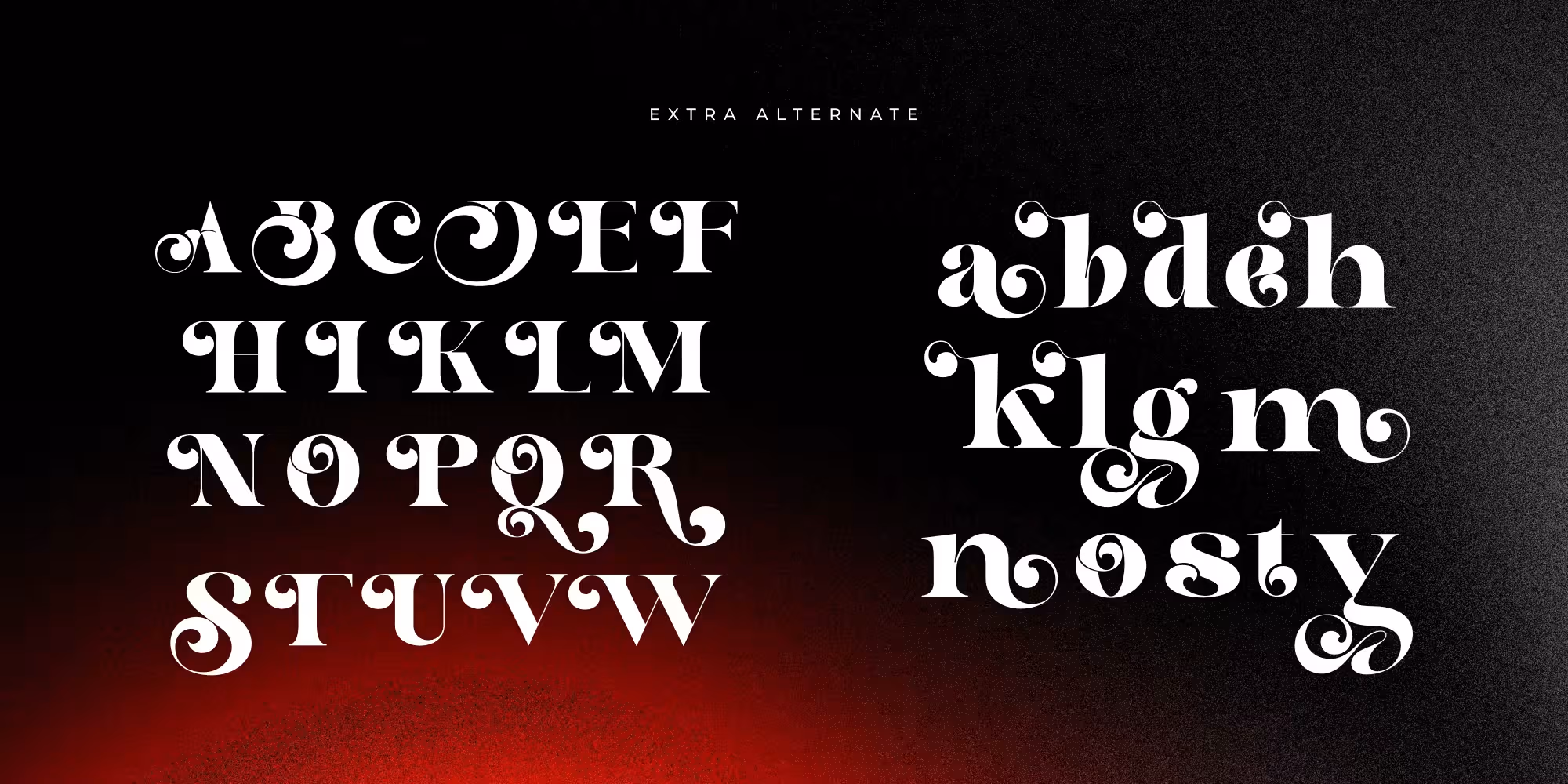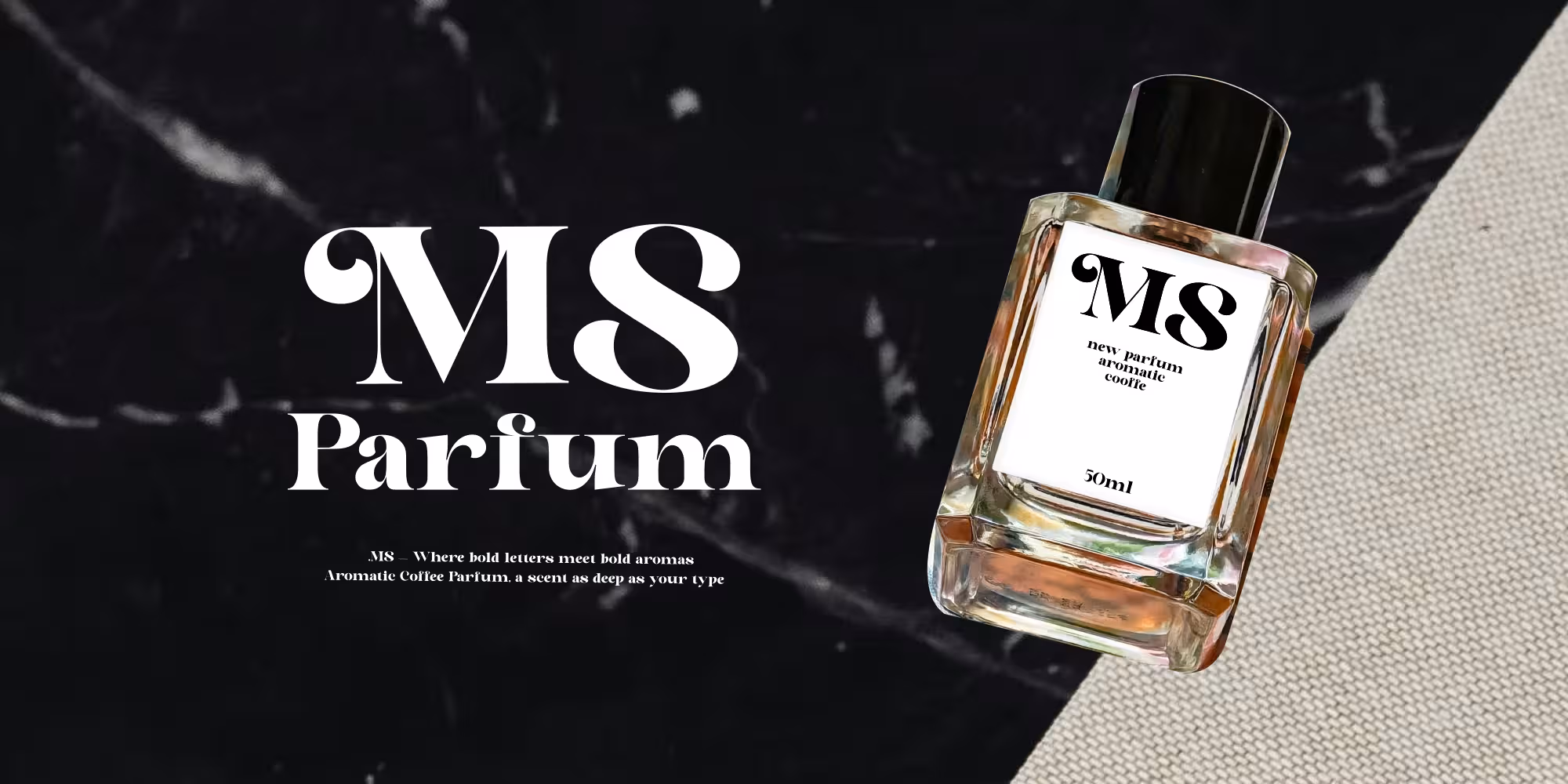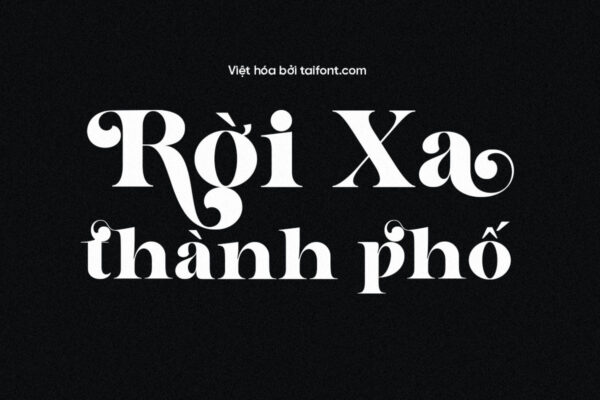
Giới thiệu về Font TF Astelin Việt hóa
TF Astelin Việt hóa là một font chữ có chân (serif) nổi bật với nét đậm, chắc chắn và đầy ấn tượng. Với thiết kế mạnh mẽ nhưng vẫn giữ được sự tinh tế và thanh lịch, font này mang đến vẻ đẹp sang trọng, đẳng cấp và rất dễ thu hút sự chú ý.
Font TF Astelin là lựa chọn lý tưởng cho các thiết kế đòi hỏi sự cao cấp và phong thái chuyên nghiệp, đặc biệt là trong lĩnh vực:
- Thiết kế logo: Hoàn hảo để tạo ra các logo mang phong cách sang trọng, vững chãi và dễ nhận diện, phù hợp với các thương hiệu muốn thể hiện sự đẳng cấp và uy tín.
- Ấn phẩm cho nước hoa: Lý tưởng để sử dụng trên bao bì sản phẩm, catalogue, hoặc các chiến dịch quảng bá nước hoa. Nét đậm và tinh tế của Astelin giúp tôn vinh sự quý phái và bí ẩn của sản phẩm, thu hút ánh nhìn của khách hàng.
Với TF Astelin Việt hóa, bạn có thể dễ dàng tạo ra những thiết kế không chỉ đẹp mắt mà còn truyền tải được thông điệp về sự tinh tế, sang trọng và đẳng cấp, góp phần nâng tầm giá trị cho thương hiệu của bạn.
Font Việt hóa TF Astelin